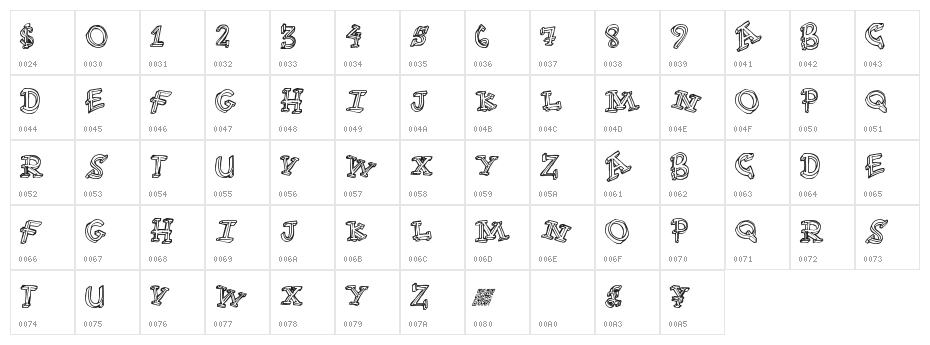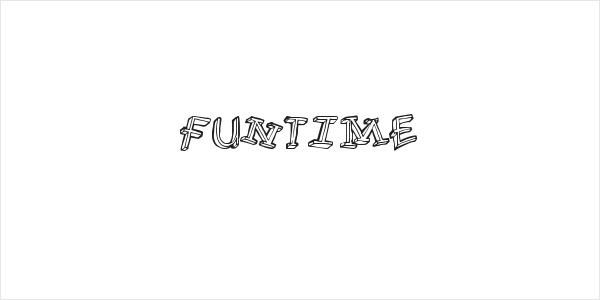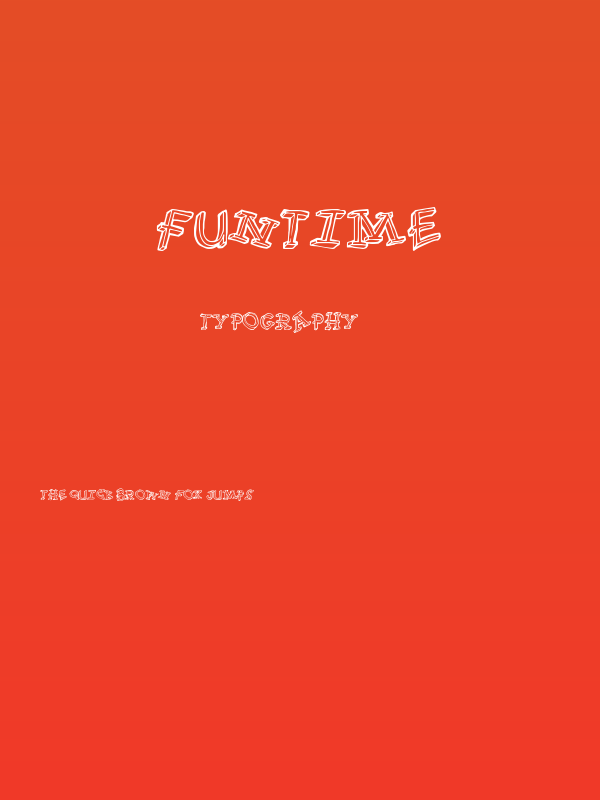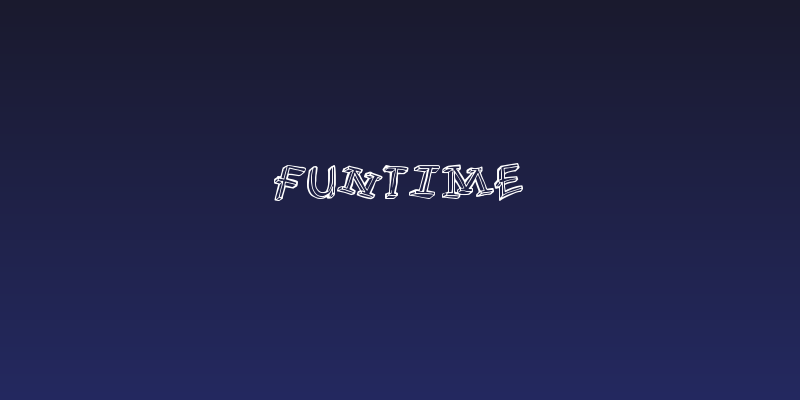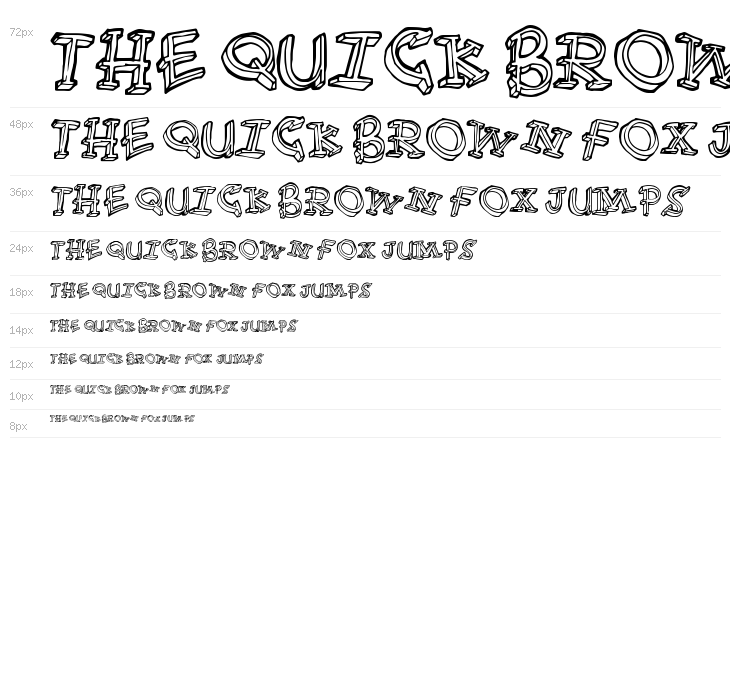
FunTime Font
✎ Decorative
| Gesamtstil | Playful, Cartoonish |
| Vorgeschlagene Projekte | Ideal for children's books, comic strips, party invitations, and playful branding. |